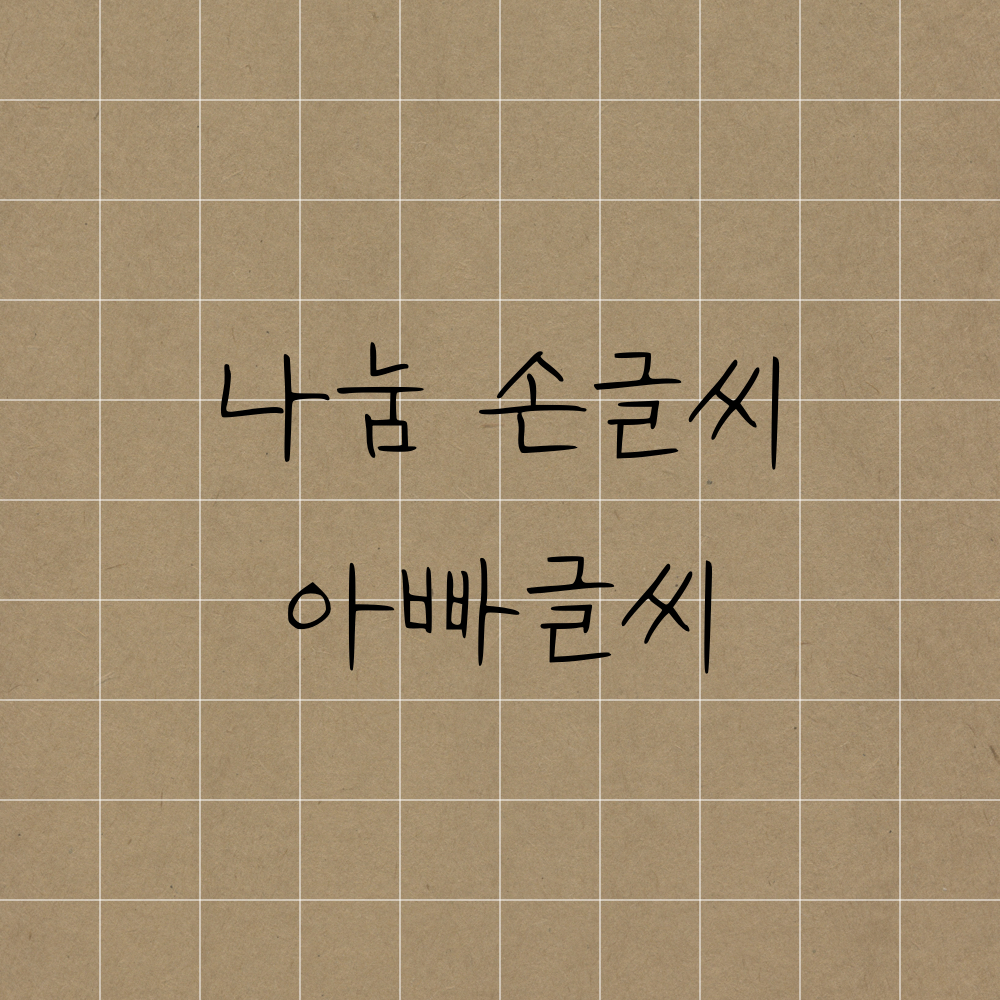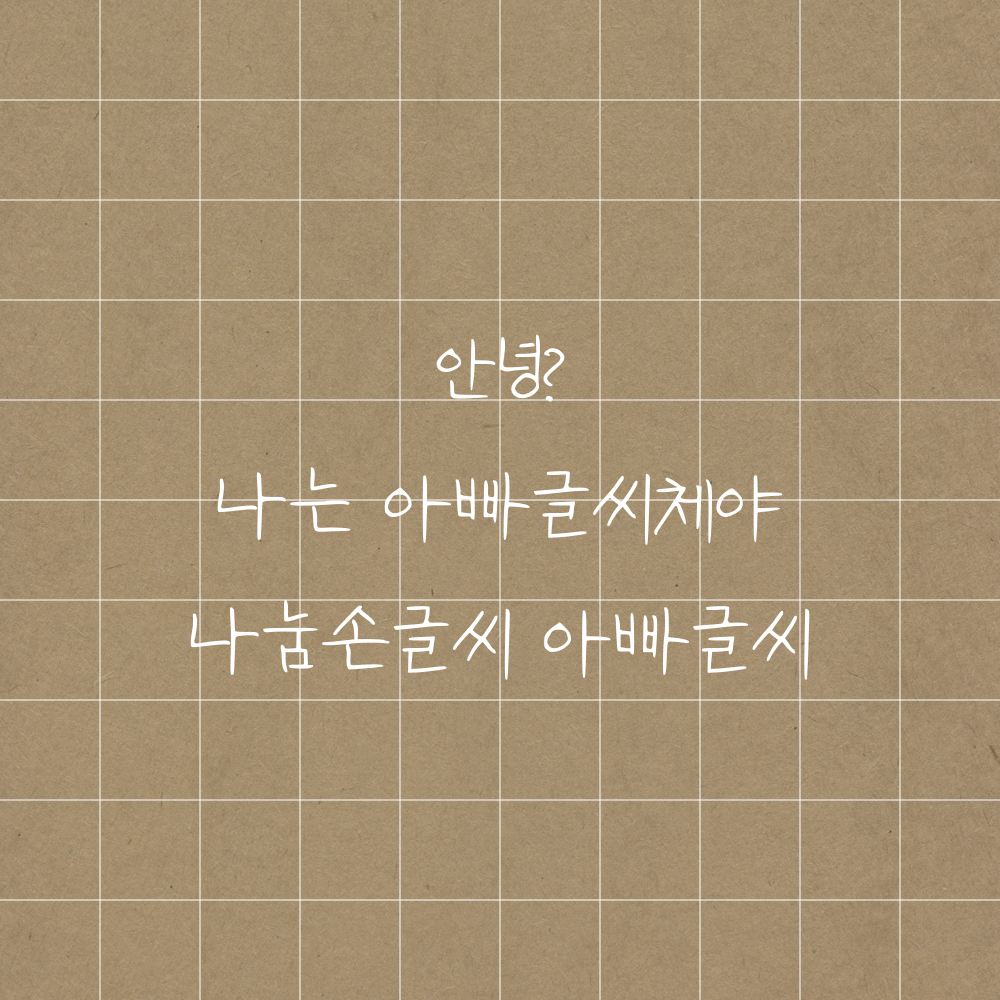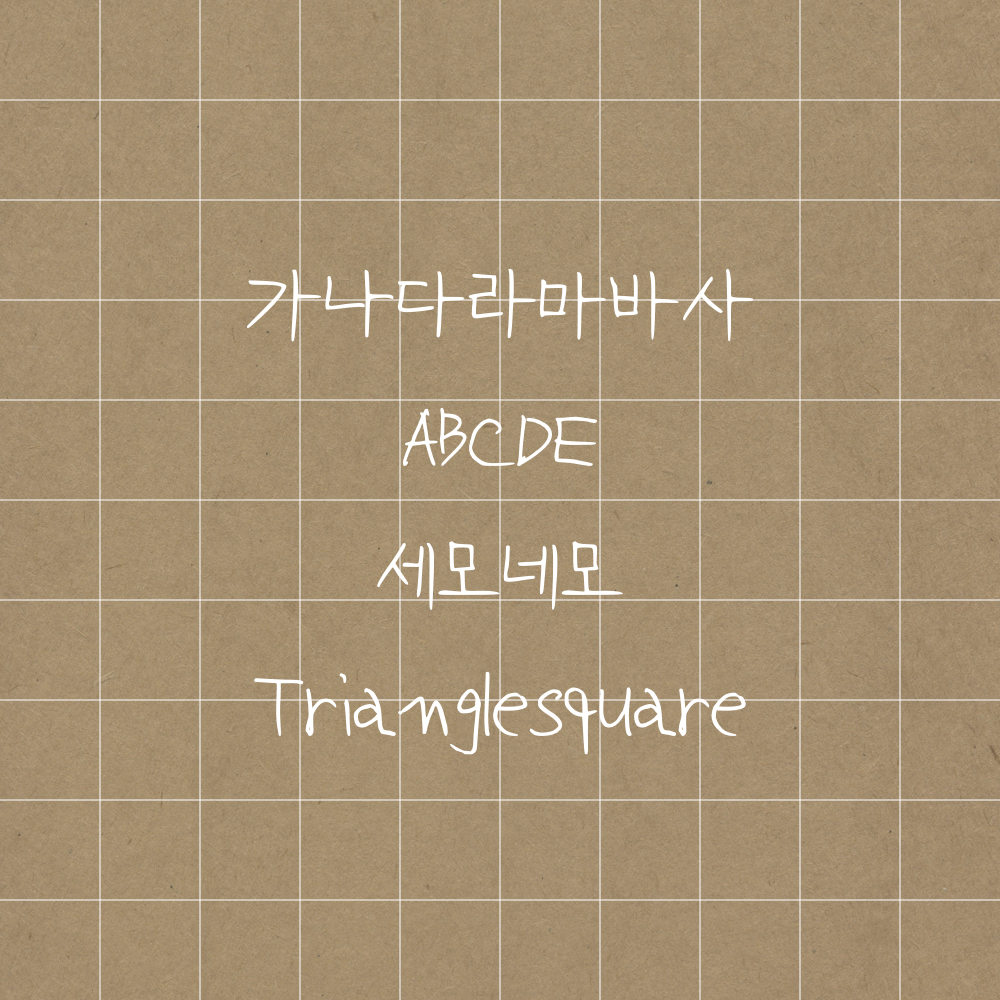
오늘의 폰트는 아빠글씨입니다💙
진짜 우리 아빠 글씨체랑 비슷해서 놀라버린 폰트🫢
반듯한듯 흘려쓰는 글씨체가 아빠 글씨체의 특징인가봅니다.
대부분의 폰트들은 글씨의 크기가 동일하기 마련인데
아빠글씨체는 그렇지 않아 손글씨체 느낌이 물씬이네요😆
필기 예시에 자주 사용하게 될 것 같네요😙 오예